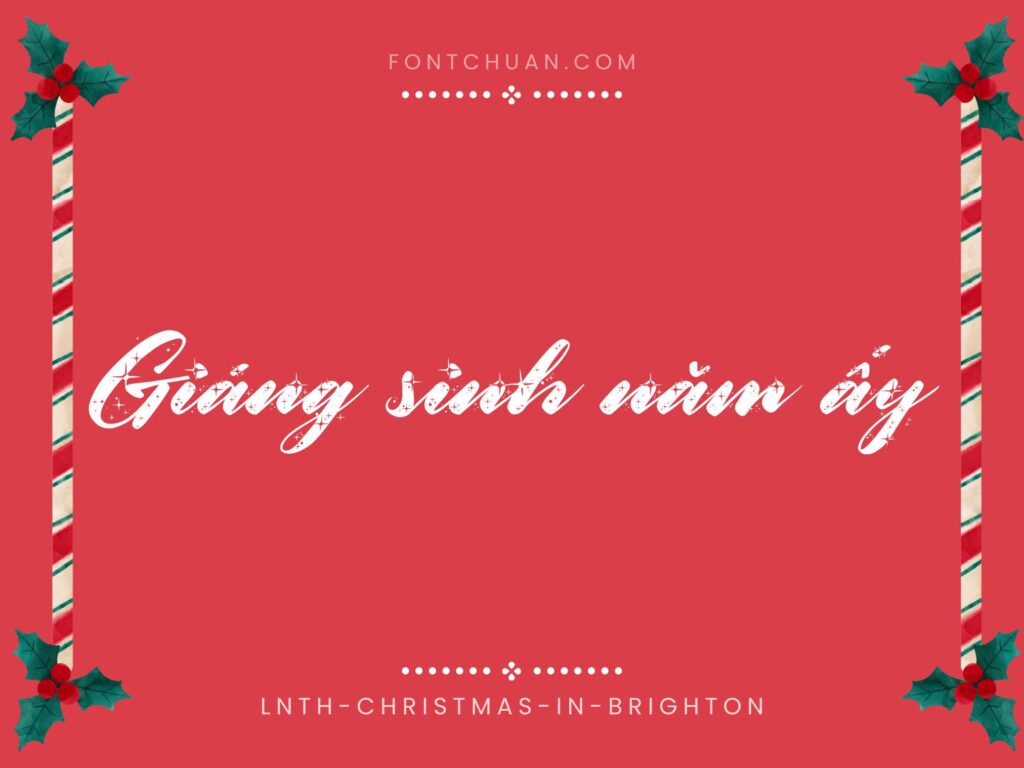
Font LNTH Christmas In Brighton Việt Hóa
Christmas in Brighton là một phông chữ viết tay độc đáo, được thiết kế bởi Cat.B, mang đậm không khí lễ hội Giáng Sinh. Phông chữ này sở hữu các đường nét mềm mại và uyển chuyển, tạo nên sự ấm áp và thân thiện cho các thiết kế liên quan đến mùa lễ hội. Nhờ được Việt hóa bởi LNTH, Christmas in Brighton hỗ trợ đầy đủ các ký tự tiếng Việt, giúp người dùng dễ dàng áp dụng trong các dự án đa ngôn ngữ. Phông chữ này đã được sưu tầm và đăng tải bởi thành viên của Font Chuẩn nhằm đáp ứng nhu cầu đa dạng của cộng đồng thiết kế.
Về đặc điểm thiết kế, Christmas in Brighton có các ký tự được thiết kế tỉ mỉ, mang lại cảm giác vui tươi và phấn khởi, phù hợp cho các dự án như thiệp mời, bìa sách, poster, logo và các ấn phẩm quảng cáo liên quan đến Giáng Sinh. Ngoài ra, phông chữ này cũng thích hợp cho các sự kiện như lễ hội, sinh nhật, Valentine và Trung thu, tạo nên không khí ấm áp và lãng mạn. Trong lĩnh vực ngành nghề, Christmas in Brighton được ứng dụng rộng rãi trong quảng cáo, thiết kế thiệp cưới, giáo dục và công nghệ, góp phần tạo nên sự độc đáo và thu hút cho các sản phẩm và thương hiệu.